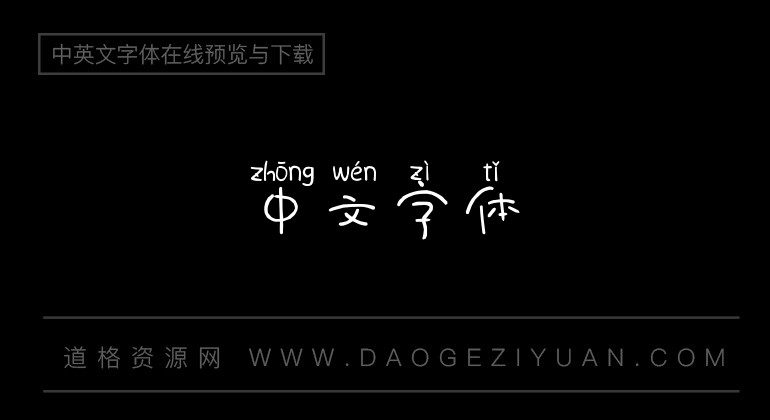
粉嘟嘟拼音体
粉嘟嘟拼音体是一款拼音字体,由粉嘟嘟文化艺术创作团队创作,以拼音声母表示汉字,让记忆拼音字母和汉字变得更容易。粉嘟嘟拼音体是一款专为小朋友设计的拼音字体,它拥有简洁、清新、可爱的外观,让小朋友们更容易记忆拼音字母和汉字。它还具有良好的可读性,让小朋友们更容易理解拼音字母的发音。
粉嘟嘟拼音体是一款非常不错的手写艺术字体,具有很好的视觉感,适合于文化类的宣传设计、商业类品牌的广告和产品包装设计以及个性化文字排版等较多场景。
粉嘟嘟拼音体字符映射图